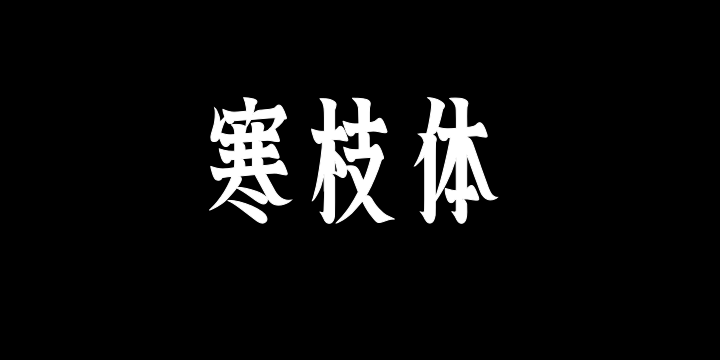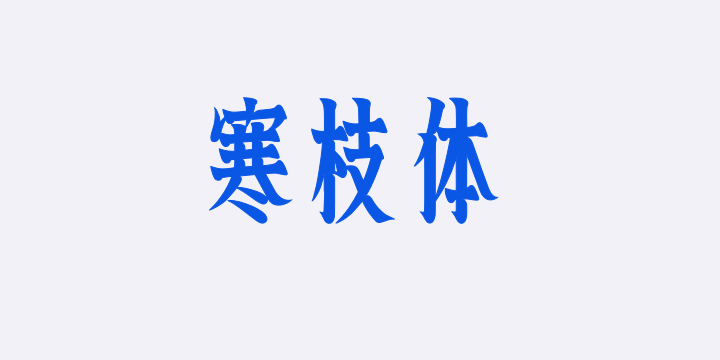
上首寒枝体 By 上首造字 商用字体
字体全名: 上首寒枝体
铸字厂: 上首造字
设计师: 胡博剑
字体简介: 上首寒枝体,简体中文约6763字。名字取自于 苏轼的“拣尽寒枝不肯栖”。该字字型劲瘦,自带清冽孤傲之感又给人留有一种冷峻雅致的印象。字体笔画似孤枝挺立寒风,尽显孤高风骨,融合了宋体的衬线雅致与手写的自然随性的笔意,使字型文雅而不刻板兼具了古朴与灵动,富有文人气息。整套字体风格统一、特点一致,字体个性鲜明,具有艺术感,适用于搭配标志、广告标语、商业广告、海报字体等高端属性。